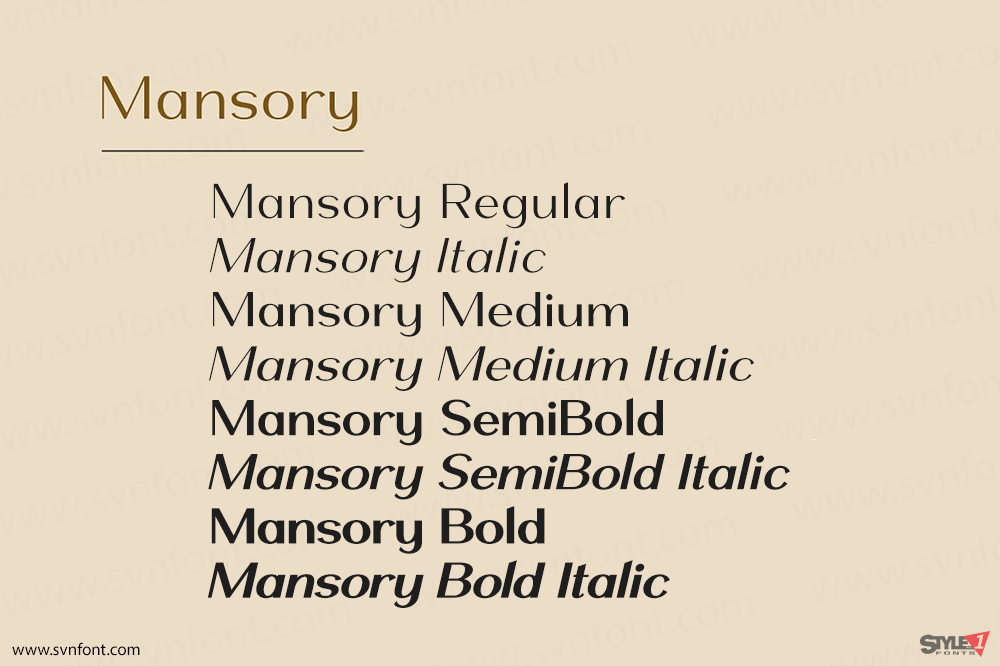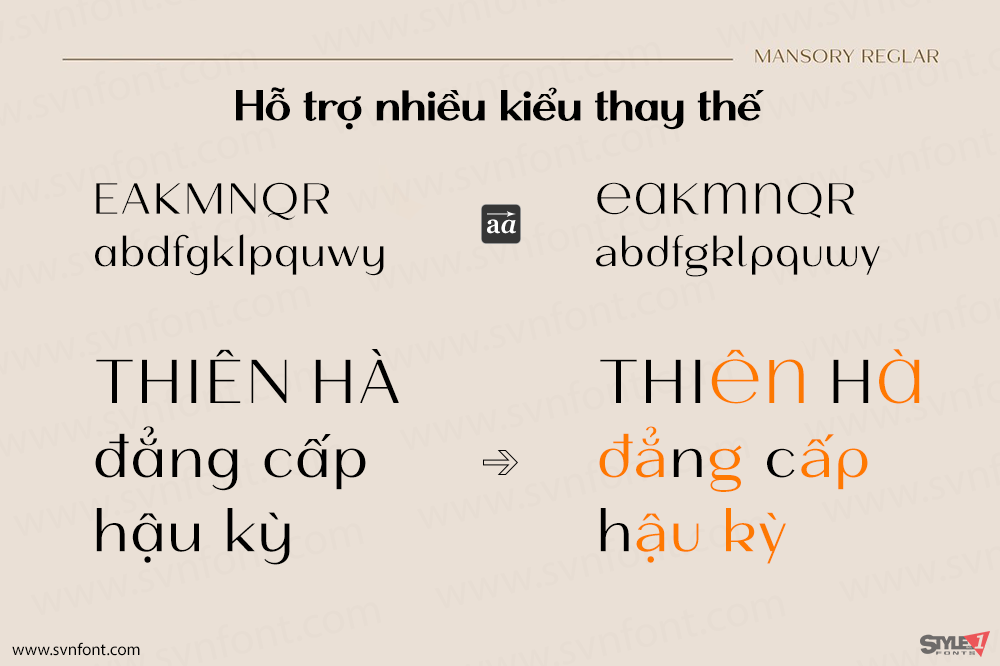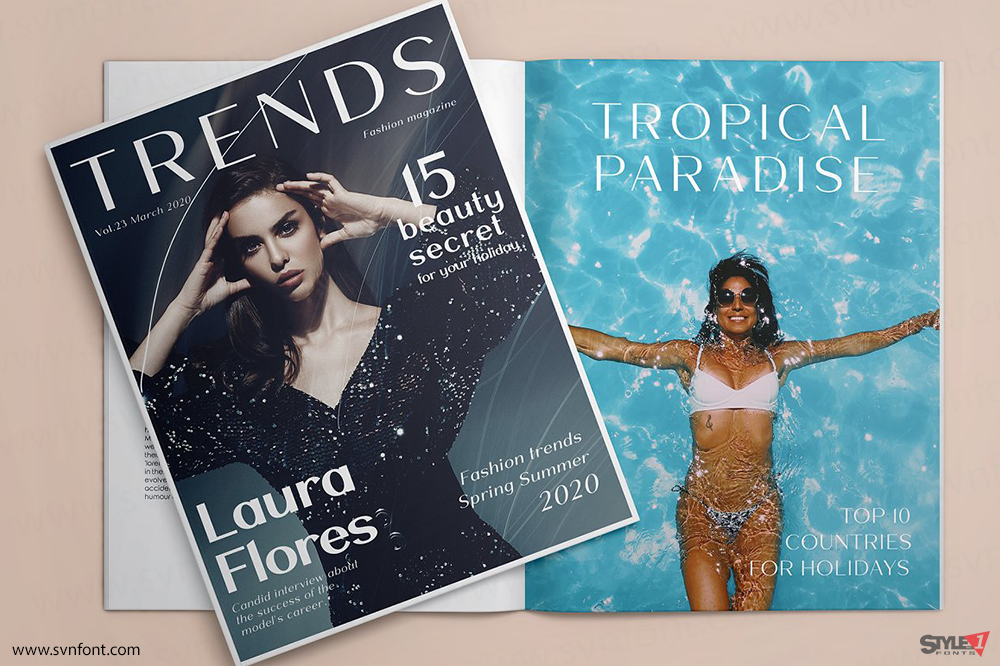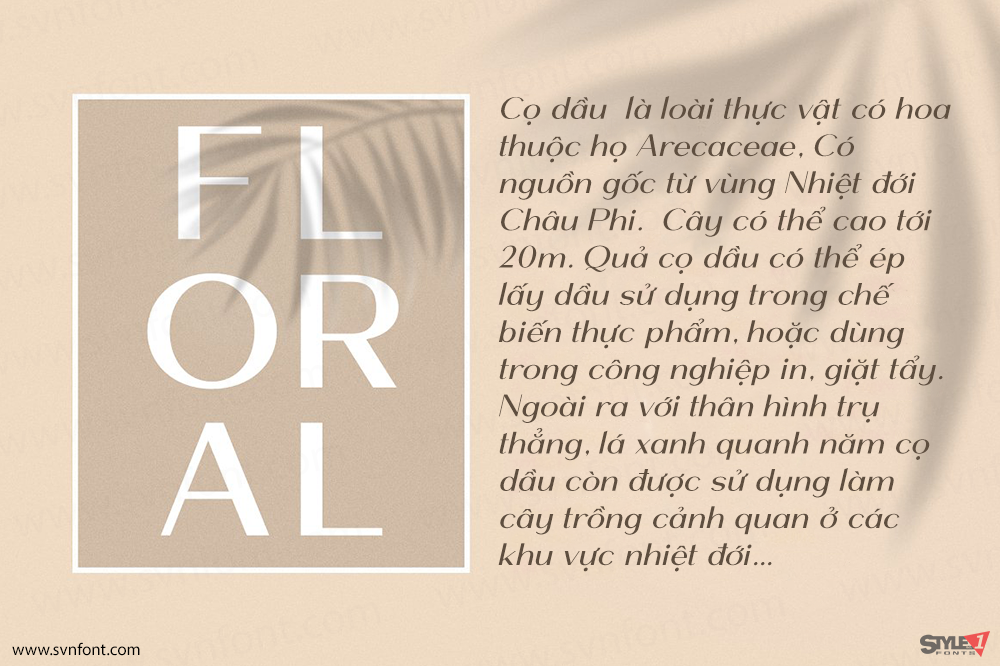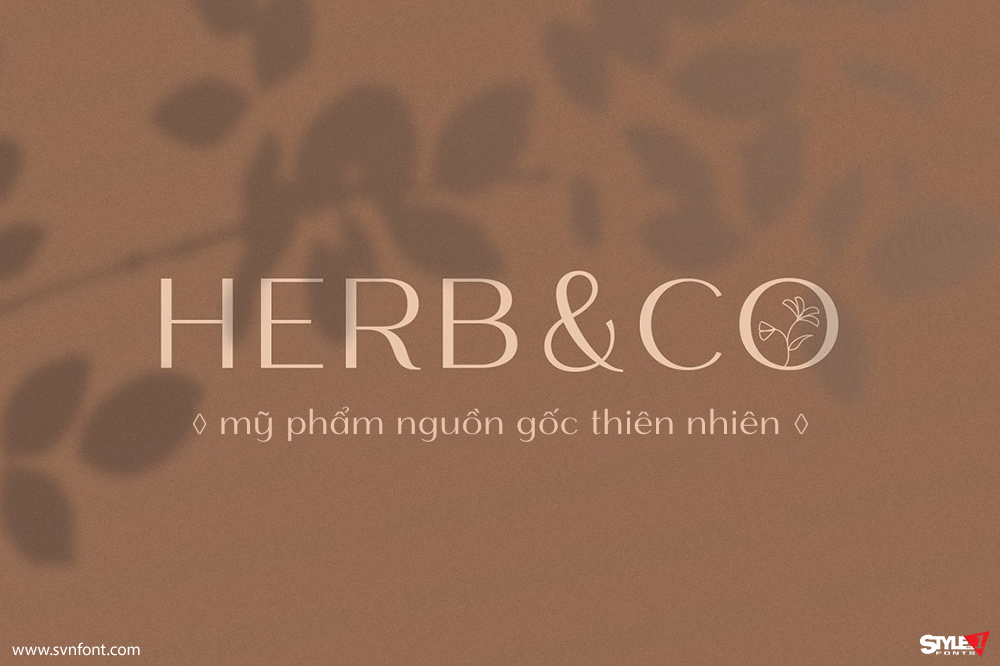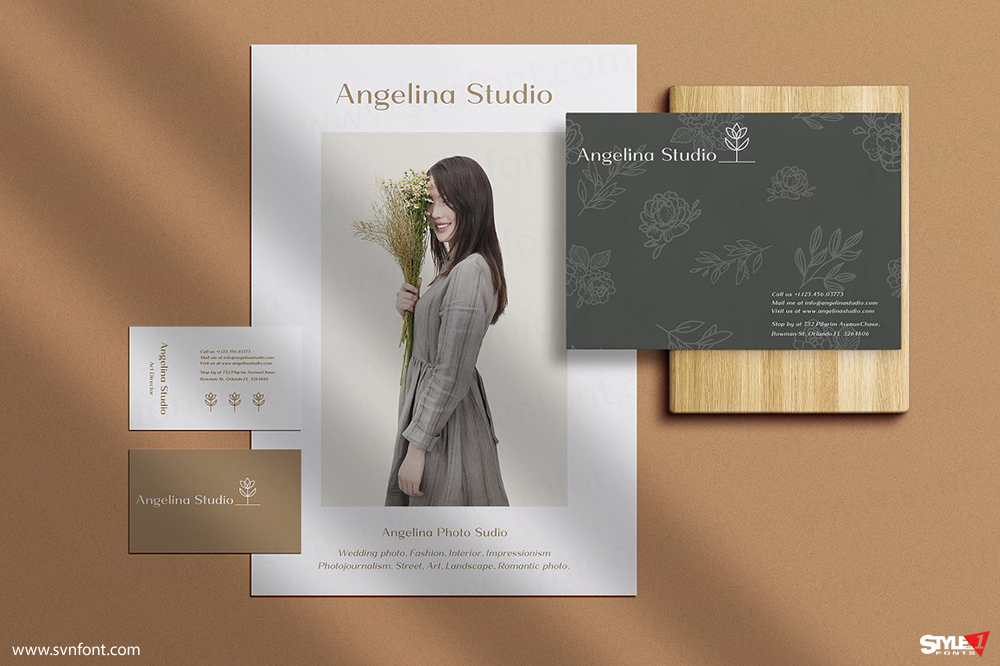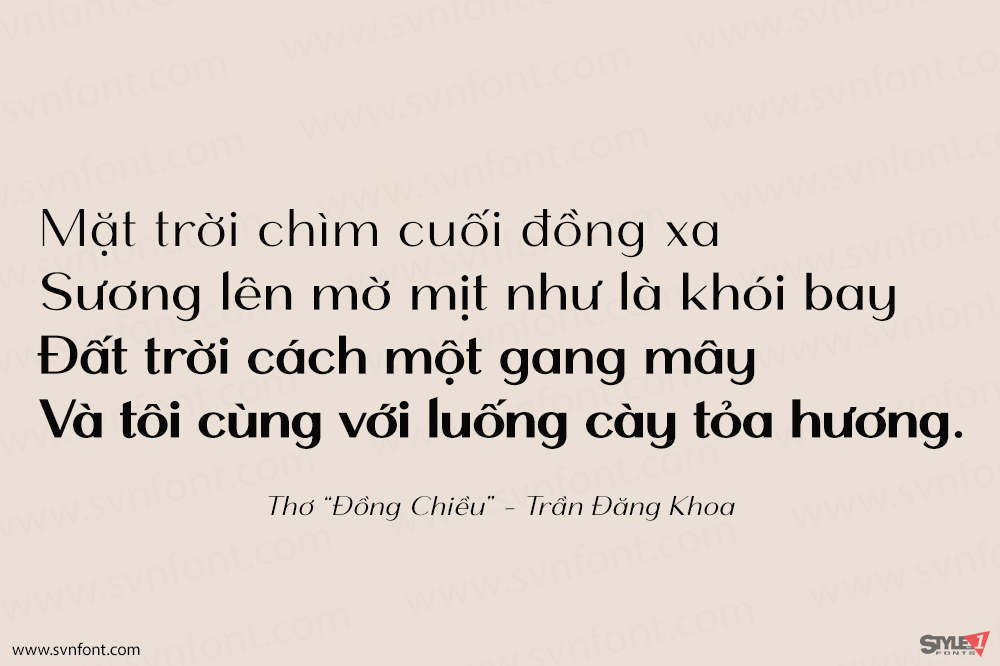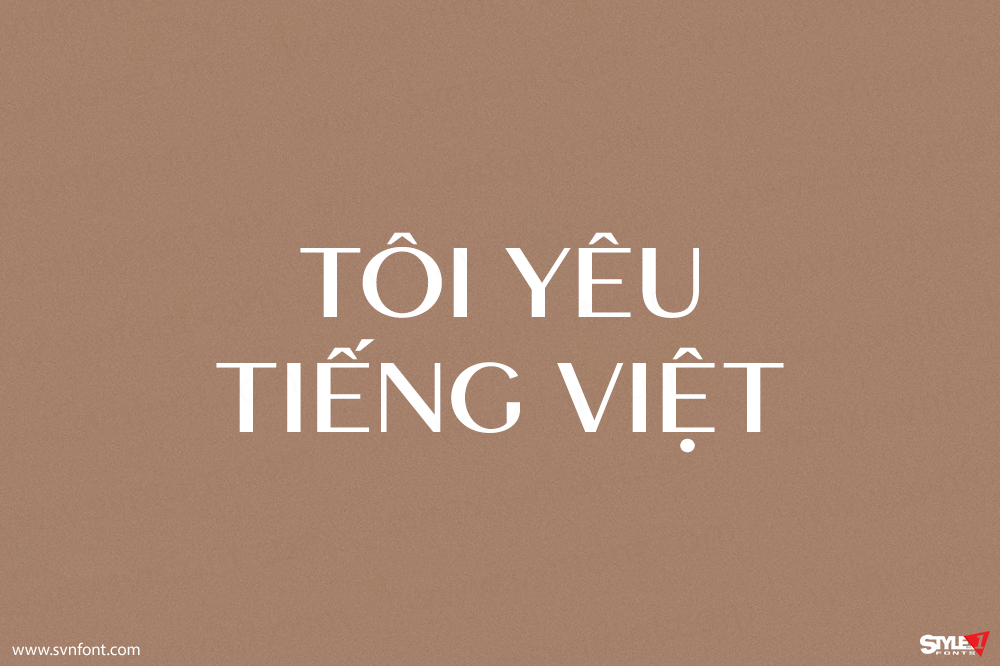
Đây là font Mansory – một kiểu chữ sans serif hiện đại, tương phản và thanh lịch, được trình bày dưới dạng thẳng đứng và nghiêng, cùng với 4 độ dày khác nhau, mang lại nhiều cơ hội hơn cho dự án thiết kế của bạn. Những đường nét tương phản và hình thức cân đối của các font này sẽ tạo sự nhận diện và dễ đọc. Kiểu Regular hoàn hảo cho văn bản, trong khi các kiểu đậm hơn lý tưởng cho logo, tiêu đề hoặc sẽ làm nổi bật chính xác những gì bạn cần. Bộ font Mansory có các ký tự thay thế theo kiểu cách (stylistic alternates) và nối chữ (ligatures) kết hợp hài hòa với font, giúp bạn làm cho dự án của mình trở nên cá tính hơn. Font này dễ sử dụng và có các tính năng OpenType.
Nhà thiết kế: Pavel Larin
Nhà phát hành: Larin Type Co.